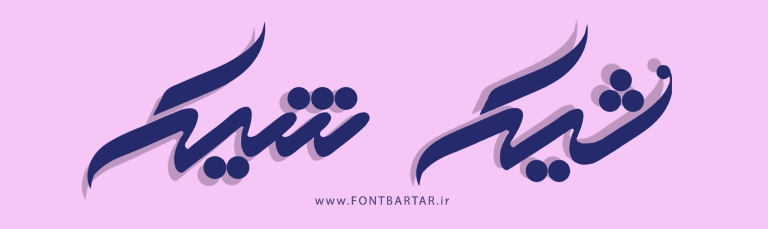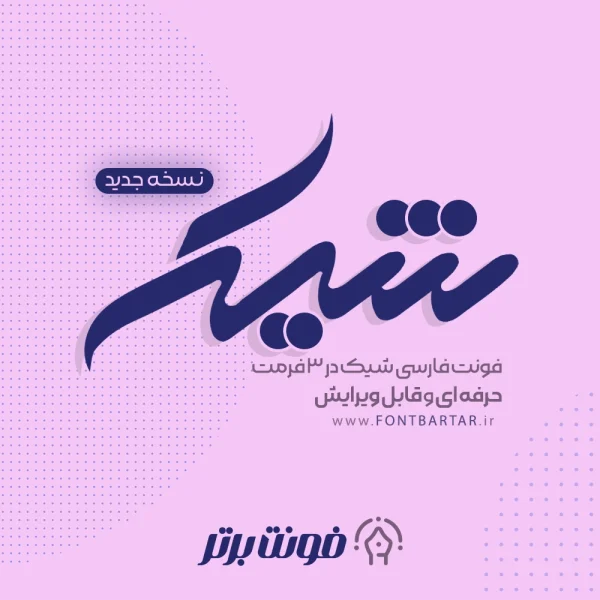
فونت شیک
فونت فارسی شیک
Shik Font
فونت فارسی شیک
فونت لوگوتایپ شیک
فونت شیک یکی دیگر از فونت های طراحی لوگوتایپ و تایپوگرافی می باشد، فونت فارسی شیک با طراحی حرفه ای و انعطاف پذیر می باشد و این امکان را فراهم می آورد که به راحتی بتوانید حروف را در کنار هم قرار دهید، با خرید فونت لوگوتایپ می توانید بدون هیچگونه دانشی لوگو تایپ طراحی کرده و تایپوگرافی های زیبایی انجام دهید و از آن کسب درآمد کنید.
📌فونت لوگوتایپ شیک:
• فونت سنگین مناسب عناوین و تیتر ها
• فونت لوگو بهترین گزینه برای تایپوگرافی پوستر ها
• گزینه مناسب برای طراحی لوگوتایپ سنگین
حروف متفاوت فونت لایه باز شیک :
حروف لایه باز فونت شیک
📌مزایای استفاده از فونت فارسی شیک:
• لوگوتایپ فارسی تمامی حروف به صورت لایه باز
• شامل تمامی حروف از الف تا ی در تمامی حالت ها